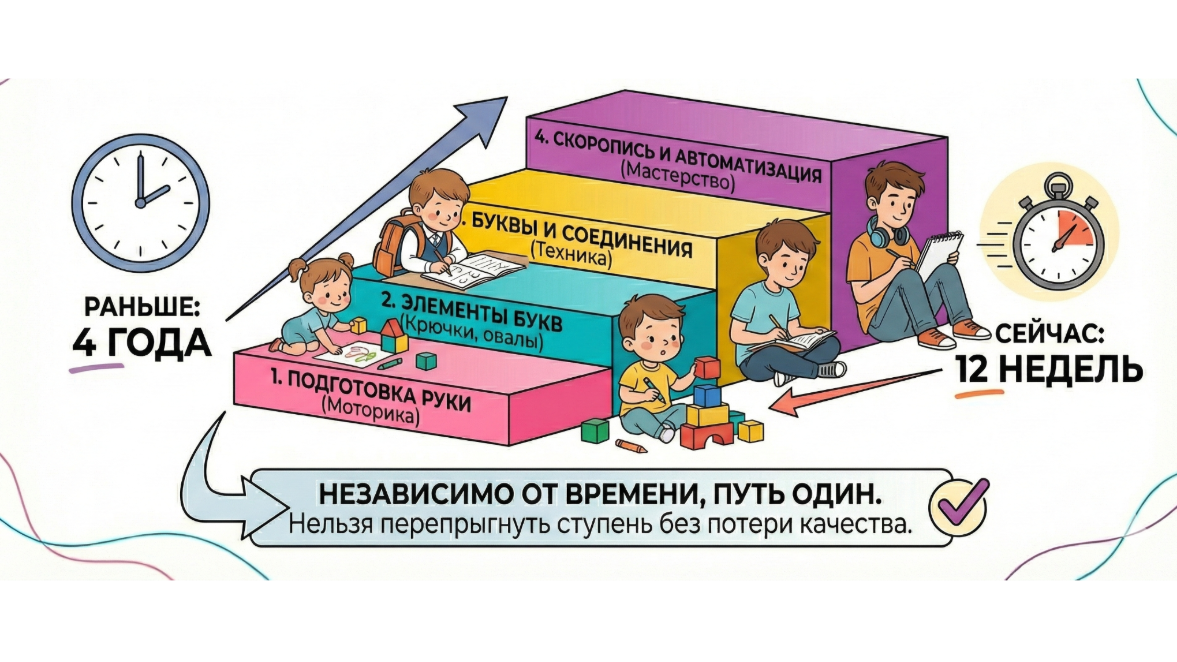
Почерк ухудшается в 1 классе? Чего ожидать от первоклассника и как улучшить почерк ребенка
Многие мамы ожидают, что, отдав ребенка в школу, они получат красивый почерк — «как в советское время». Но реальность современной школы сурова: уроки письма и уроки чистописания теперь длятся всего 12 недель вместо прежних 4 лет.
Это всего 3 месяца на освоение сложнейшего навыка, который требует созревания мозга и тысяч повторений. Именно поэтому плохой почерк у ребенка к середине года становится самой частой сложностью для родителей и малышей.
Почему ребенок пишет неразборчиво: ожидание родителей vs реальность
Родители ждут ровных строк и правильных соединений. Но что мы видим в тетрадях к середине первого класса?
Буквы «пляшут», наклон хаотичный, рука ребенка дрожит от напряжения, а скорость письма ребенка падает.
Почему так? Потому что за 12 недель невозможно автоматизировать процесс. Современная система образования практически не дает полноценное обучение красивому письму — она лишь проверяет, как вы научились писать дома или в саду.
Это не хорошо и не плохо — это реалии, в которых мы сегодня растим и обучаем детей.
Плохой почерк у ребенка: главные трудности первоклассника
Из моей практики работы с более чем 10 000 семьями я вижу три основные сложности у младших школьников:
1. Зажим.
Ребенок давит на ручку при письме так сильно, что пальцы белеют, рука быстро устает. Энергия уходит в избыточное давление ручки при письме, а не в сам процесс выведения букв. В итоге — усталость через 5 минут и слезы над домашним заданием.
2. Неправильное направление букв.
Ребенок не понимает алгоритм построения письменных букв. Особенно это видно на букве О и всей овальной группе. Он «рисует» букву так, как запомнил визуально, часто в обратную сторону. Это замедляет письмо в разы.
Попросите прямо сейчас написать слово «СОВА» и понаблюдайте, как ребенок пишет его. А затем сравните со своим письмом. В большинстве случаев родители замечают разницу.
3. Потеря мотивации.
Из-за постоянных замечаний «Старайся лучше» ребенок не хочет писать, формируется страх ошибки. Современные дети более чувствительны к критике. Это приводит к слезам над тетрадью и негативному отношению к учебе.
Как помочь ребенку улучшить почерк: советы маме
Самое важное — понять: ребенок не ленится. Он находится в системе, которая не дает достаточно времени для формирования навыка.
К середине первого класса ребенок может писать чисто, если у него есть база: расслабленная постановка руки для письма и понимание алгоритма овальных движений.
Если базы нет, проблема сама не исчезнет. Позже может потребоваться коррекция почерка у ребенка.
Хорошая новость в том, что ситуацию можно изменить мягко и без давления. Домашние игровые уроки каллиграфии с кистью и игровые упражнения для письма помогают снять зажим и вернуть ребенку ощущение легкости.